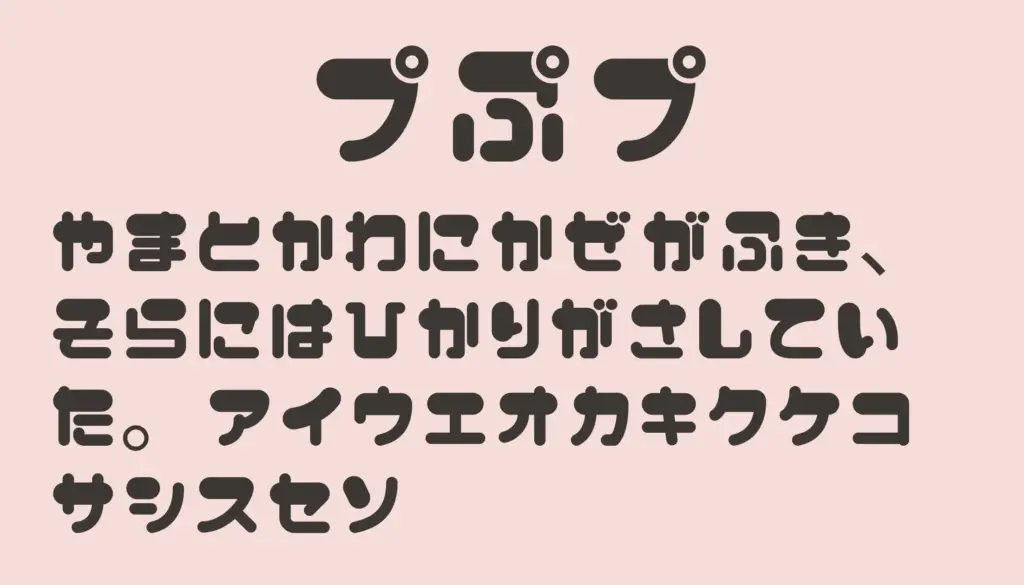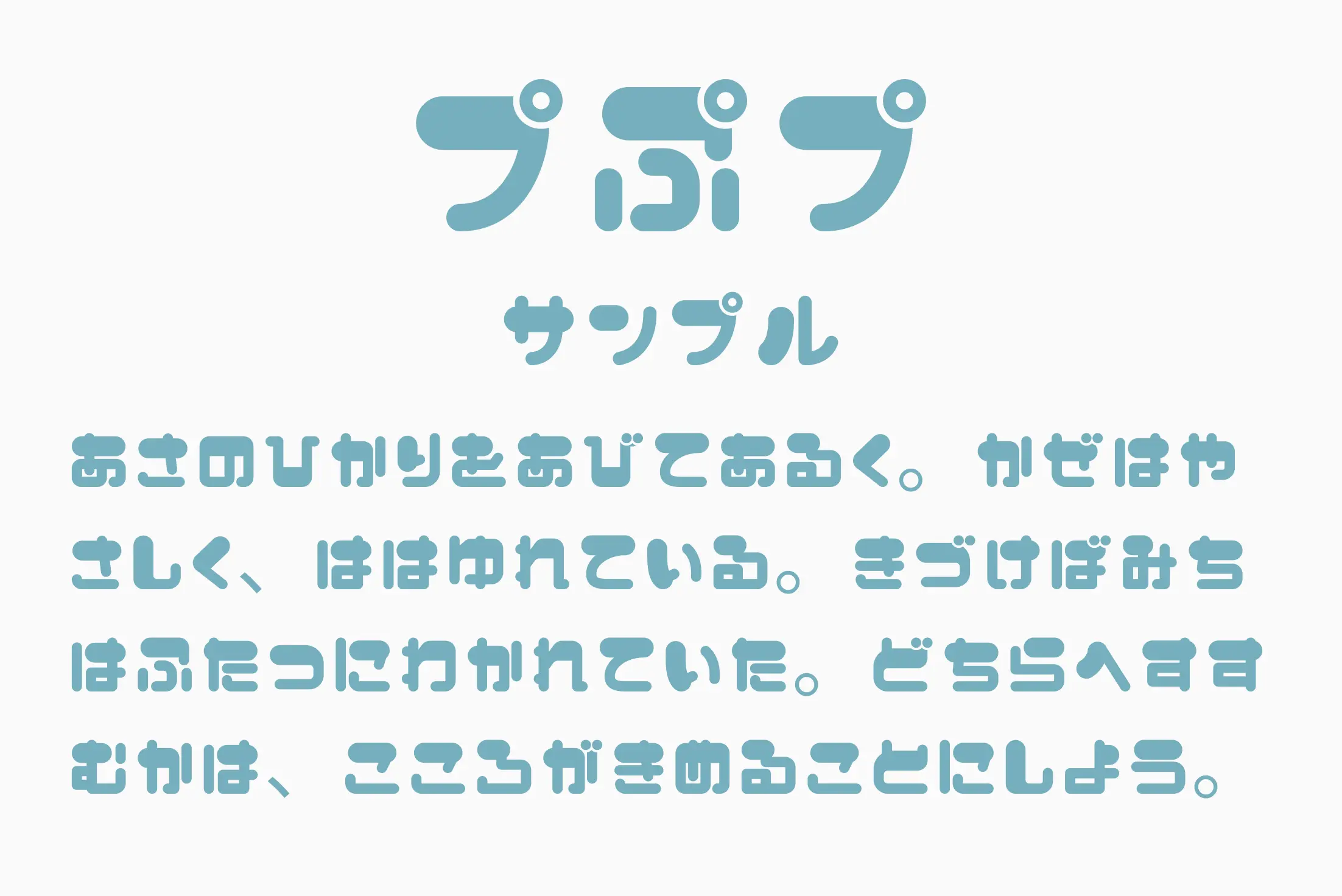
その名のとおり「ぷ」に特化したような、ふんわりとした丸みと柔らかさが魅力のディスプレイ系フォント。文字全体に遊び心があり、ぽよぽよとした見た目が特徴です。POPや装飾用途、応援うちわ、幼児向けコンテンツなど、楽しくやさしい雰囲気を出したい場面にぴったり。可読性もありながら、文字に“抜け感”や“ゆるさ”があるため、カジュアルで親しみのあるデザインに仕上がります。
プぷプ